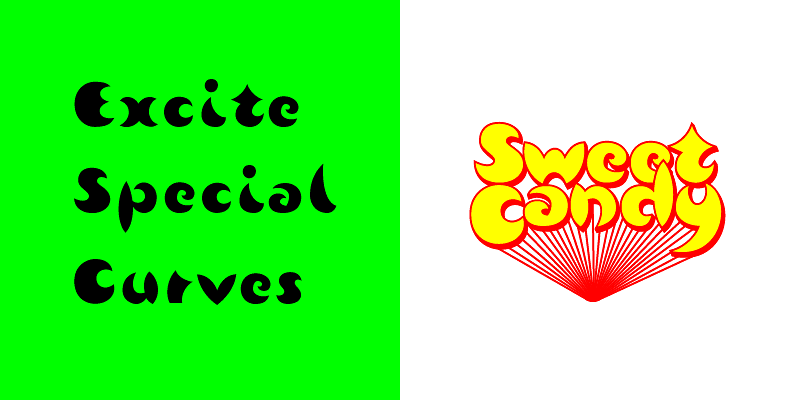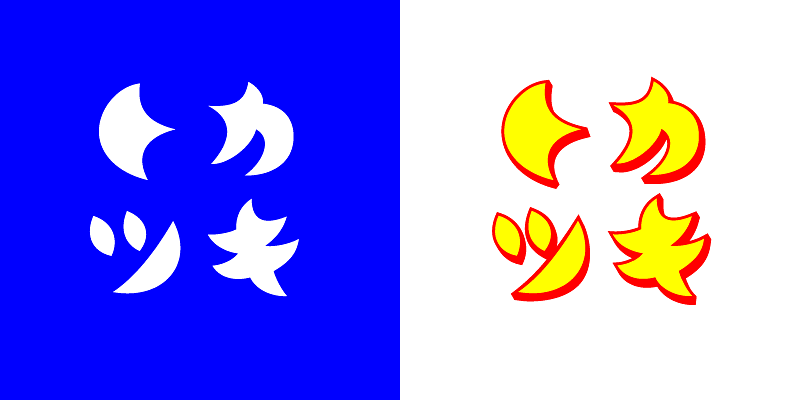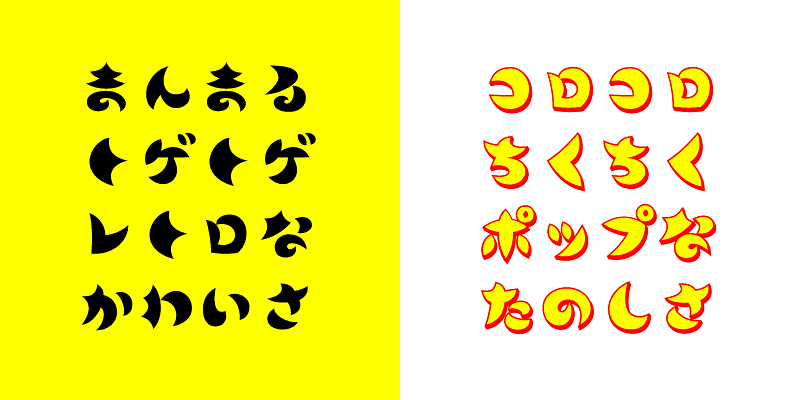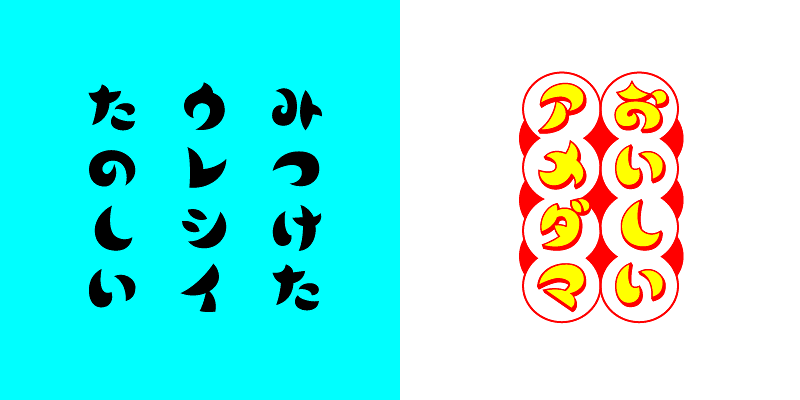
Diese Schrift zeichnet sich durch runde, geschwungene Striche mit scharfen Spitzen aus. Wäre sie nicht ideal für einen Schriftzug oder eine auffällige Schlagzeile? Die entsprechende Farbschriftversion ist vergnüglich und fröhlich und springt aufgrund ihres 3D-Effekts bei den Rot- und Gelbtönen ins Auge.